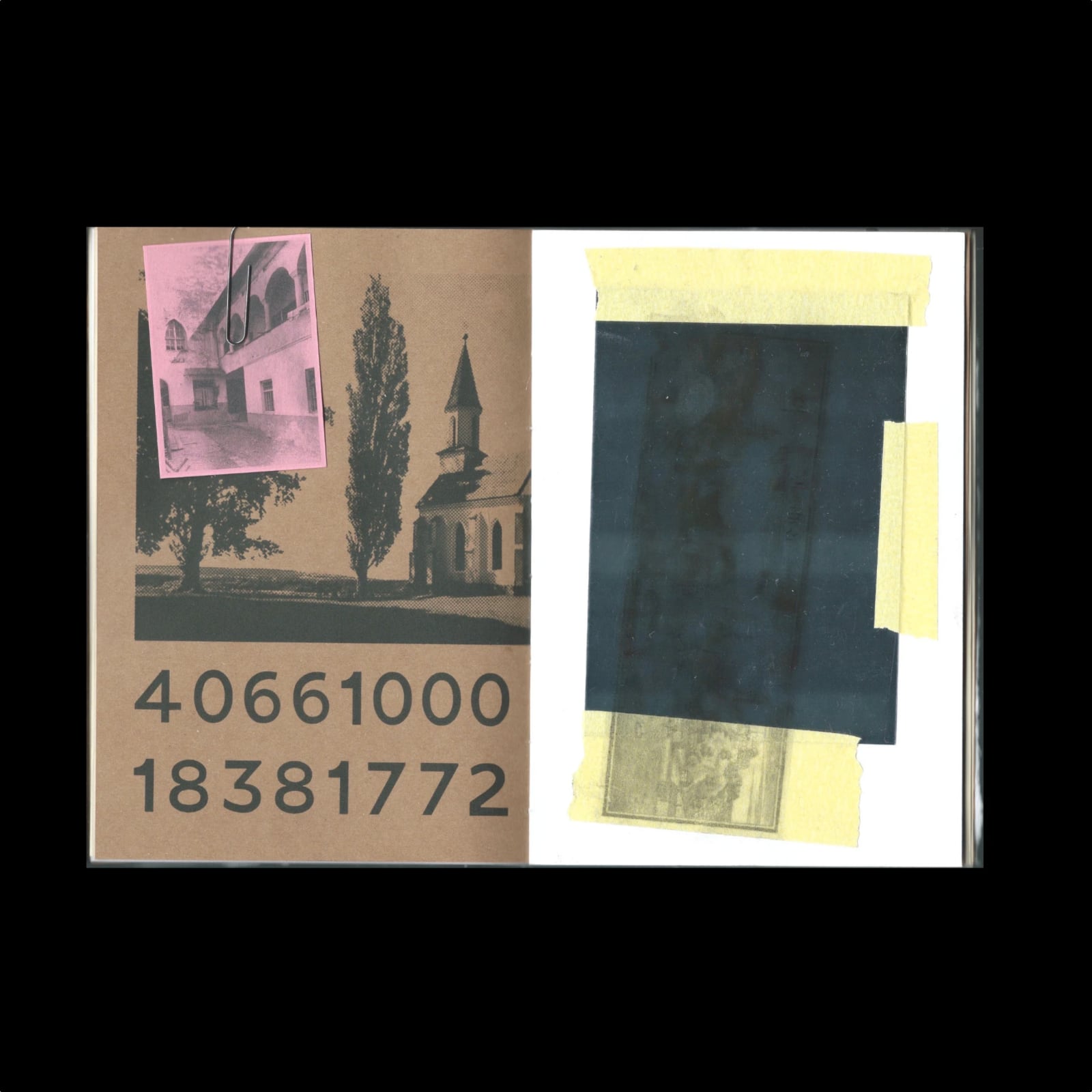
Editorial de tipografía de muestra medieval de fuente variable Kraiberg
Este editorial tipográfico de muestra medieval de fuente variable muestra Kraiberg, una familia histórica de fuentes de exhibición diseñadas por Laura Lackner.
Los editoriales tipográficos de muestras medievales de fuente variable de Laura Lackner transforman la estructura arquitectónica de los códices de las iglesias en tipos de visualización dinámicos. Estos tipos de letra llevan el peso de los manuscritos medievales, combinando los ángulos adyacentes de negrita con la flexibilidad de los ejes variables contemporáneos. En lugar de limitarse a presentar tipos de letra en formato digital, Lackner produjo tipos de letra físicamente variables para editoriales tipográficas de muestras medievales. Esta ejecución manual utiliza una impresora de inyección de tinta doméstica y teclas de máquina de escribir para establecer una estética de archivo original. El diseño resultante se siente como una colección de documentos históricos no descubierta, donde las pautas de diseño de la cuadrícula estructural se rompieron intencionalmente para explorar la fricción visual.
Editorial de tipografía de muestra medieval de fuente variable
La curación táctil define la producción impresa, utilizando diferentes capas de papeles y materiales para crear colecciones de documentos físicos. La página equilibra gráficos de palabras técnicas y tablas de peso variable con pliegos abstractos y experimentales que priorizan el sangrado de tinta orgánica sobre la legibilidad pura. Al utilizar el papel varias veces con una impresora doméstica estándar, Lackner creó una alineación desplazada y niveles de saturación de tinta únicos. Este editorial de tipografía de muestra medieval de fuente variable táctil muestra cómo el diseño tipográfico digital puede beneficiarse de una traducción física e imperfecta. Cuando se presionan contra las fibras granuladas del papel elegido, las letras en negro puro añaden profundidad, transformando la muestra digital en un artefacto físico.
En última instancia, la publicación sirve como catálogo funcional y como sistema visual. La tensión estructural entre geometrías vectoriales limpias y texturas de papel en bruto resalta nuevas tendencias en archivos. Lackner estableció un lenguaje de diseño sistemático en el que la penetración de la tinta y las impresiones de la máquina de escribir se convirtieron en parte de la identidad tipográfica. El editorial tipográfico de muestra medieval de fuente variable demuestra cómo las referencias históricas y las texturas simuladas pueden enriquecer la tipografía contemporánea. Ver proyecto directamente El portafolio de Laura Leckner.